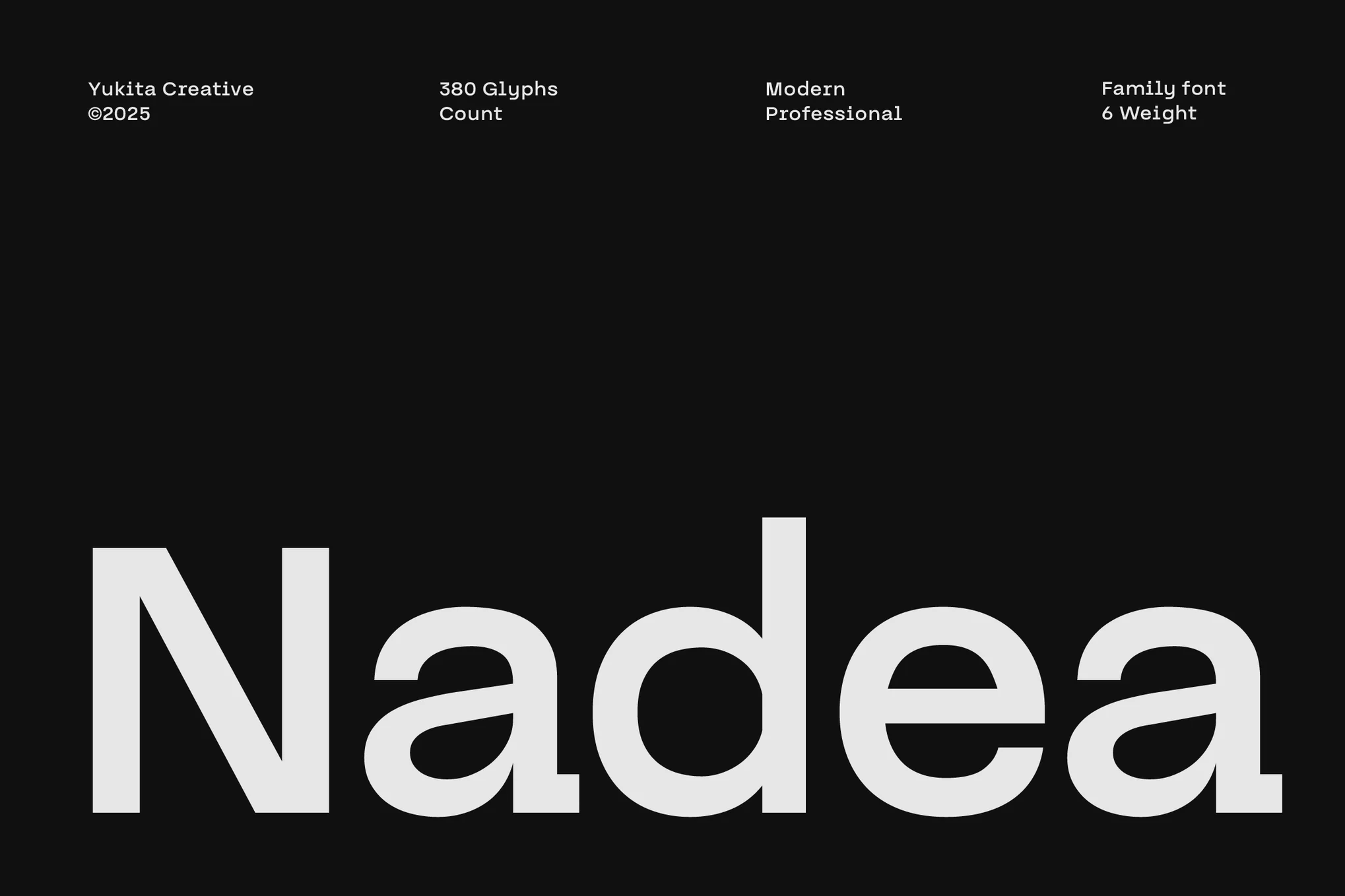
Nadea Sans Serif را معرفی می کنیم، حروفی مدرن و مینیمالیستی که برای آوردن ظرافت و سادگی به پروژه های خلاقانه شما ساخته شده است. با خطوط تمیز، نسبتهای متعادل و وزنهای متنوع، Nadea برای برندسازی، لوگو، طراحی سرمقاله، پوستر و طراحی وب بسیار مناسب است.
Nadea با دقت با توجه به جزئیات طراحی شده است، ظاهری معاصر ارائه می دهد که هم تیترهای برجسته و هم متن ظریف بدن را بهبود می بخشد. چه روی پروژههای برندسازی مدرن، طرحبندیهای تایپوگرافی یا طراحی UI/UX کار میکنید، Nadea Sans Serif انعطافپذیری، دقت و کیفیت حرفهای را در هر شخصیت ارائه میدهد.